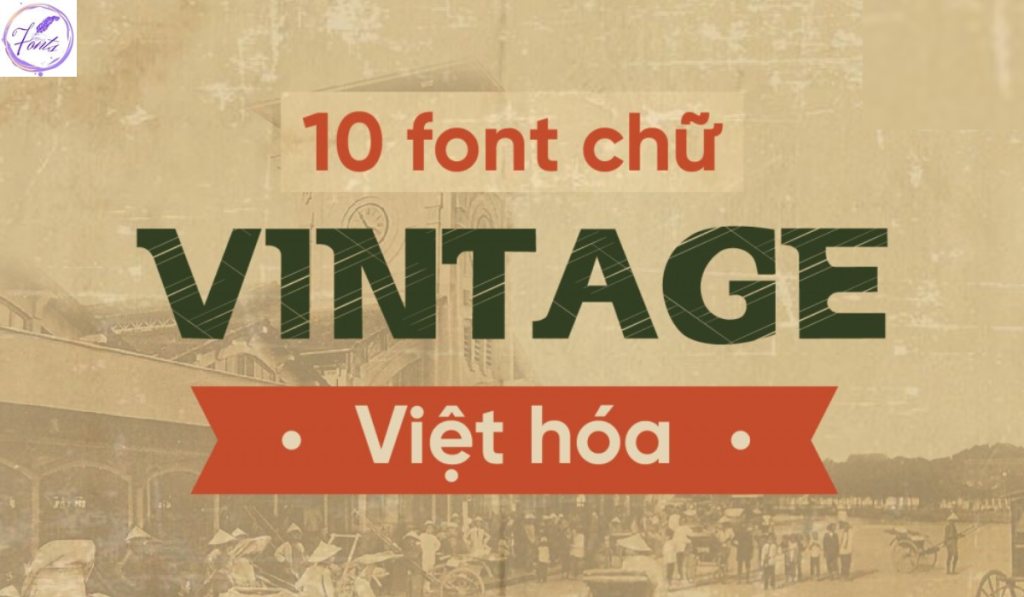
Font chữ cổ điển việt hóa
Phân loại: Cổ điển, hoài cổ, vintage, retro
Kiểu chữ: Có chân, không chân
Độ dày: Thin, Light, Regular, Bold, Black
Font chữ cổ điển việt hóa mang đến sự thanh lịch và trang trọng, thường được sử dụng trong các tài liệu có tính chất lịch sử hoặc pháp lý. Với việc bổ sung các ký tự tiếng Việt, font này không những giữ nguyên được vẻ đẹp thẩm mỹ của phông chữ cổ điển mà còn tăng cường khả năng ứng dụng tại Việt Nam. Đây là sự lựa chọn hoàn hảo cho những ai muốn kết hợp yếu tố văn hóa Việt với phong cách cổ điển quý phái.
Đánh giá font chữ cổ điển việt hóa
Font chữ cổ điển việt hóa được đánh giá cao bởi sự tinh tế và khả năng thích ứng cao. Nó không chỉ làm nổi bật vẻ đẹp của các tác phẩm văn học, pháp lý mà còn được ưa chuộng trong thiết kế trang trí và mỹ thuật. Khả năng tương thích với các ứng dụng đồ họa hiện đại làm tăng giá trị sử dụng của font này trong nhiều dự án khác nhau, từ in ấn đến số hóa.